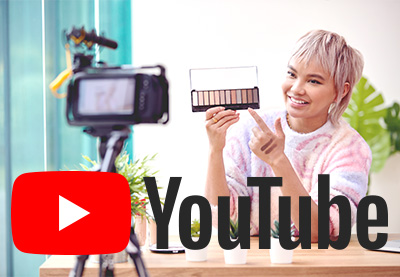
Welchen Font nutzt Youtube?
Es mag wie eine einfache Frage erscheinen: „Welche Schriftart verwendet YouTube?“ Aber die Antwort ist überraschend kompliziert, weil es verschiedene YouTube-Schriftarten gibt. Wir werden Ihnen in diesem Artikel alles erklären und einige alternative YouTube-Schriftarten durchgehen.
Welche Schriftart verwendet YouTube?
Die Schriftarten von YouTube variieren je nachdem, ob Sie über das Logo, Videotitel, Kommentare oder andere Bereiche der Website sprechen. Lassen Sie uns das nacheinander durchgehen.
Welche Schriftart verwendet YouTube für Videotitel?
Das ist recht einfach. Für Videotitel verwendet YouTube Roboto, eine sehr lesbare Schriftart, die Google für verschiedene Dienste wie Android, Google Maps und Google Play verwendet.
Beispiel der Schriftart Roboto via Wikimedia Commons
Welche Schriftart verwendet YouTube für Kommentare?
Für Videobeschreibungen und Kommentare verwendet YouTube auch Roboto. Bisher also alles einfach.
Welche Schriftart verwendet das YouTube-Logo?
Die Schriftart des YouTube-Logos sieht jedoch ganz anders aus als die Schriftart, die in den Kommentaren oder Videotiteln verwendet wird. Das liegt daran, dass es sich um eine völlig andere Schriftart handelt, und sie heißt YouTube-Logo.
Youtube-Logo-Schriftart
Youtube-Logo-Schriftart. Quelle: Wikipedia
Sie ist viel fetter und ziemlich kondensiert und ist tatsächlich eine modifizierte Version von Alternate Gothic, einer Schriftart, die Morris Fuller Benton im Jahr 1903 entworfen hat. Das Logo selbst wurde von YouTube-Mitbegründer Chad Hurley im Jahr 2005 entworfen.
Warum verwendet das YouTube-Logo eine andere Schriftart? Wie einer der Designer erklärt, erwies sich die neue YouTube-Schriftart als zu stark von dem ursprünglichen Logo abweichend, sodass sich das Unternehmen entschied, beim bestehenden Logo zu bleiben „als Hommage an unsere Vergangenheit“.
Um die Dinge noch etwas komplizierter zu machen. Es gibt auch verschiedene Versionen des YouTube-Logos für verschiedene Dienste, und einige verwenden überhaupt keinen Text. Hier ist zum Beispiel das Logo von YouTube Shorts:
Youtube-Shorts-Logo
Youtube-Shorts-Logo. Quelle: Wikipedia
Und was ist mit YouTube Sans?
YouTube hat auch eine eigene benutzerdefinierte Schriftart namens YouTube Sans, die es in Zusammenarbeit mit verschiedenen Designagenturen erstellt und 2017 eingeführt hat. Die Schriftart lässt sich von dem berühmten Wiedergabesymbol inspirieren und verwendet den gleichen Winkel, um Schnitte in einigen der Buchstabenformen zu erzeugen.
YouTube Sans
YouTube Sans. Quelle: Google Design
Das YouTube-Designteam hat im Laufe der Jahre seit 2017 subtile Änderungen an YouTube Sans vorgenommen, wie z. B. das Hinzufügen von abgerundeten und kursiven Versionen. Hier ist die YouTube-Schrift kursiv und abgerundet:
YouTube-Schrift kursiv und abgerundet
YouTube-Schrift kursiv und abgerundet. Quelle: Google Design
YouTube verwendet YouTube Sans tatsächlich nicht für sein Logo oder die Videotitel, Beschreibungen und Kommentare, aber es verwendet es in vielen seiner Marketingmaterialien und für andere Dienste außerhalb regulärer YouTube-Videos. Hier ist zum Beispiel die Landingpage von YouTube TV, die YouTube Sans für die eindrucksvollen Überschriften und Roboto für den Fließtext verwendet.
Youtube-TV-Seite
Nun, da wir alle Ihre Fragen zu den verschiedenen Schriftarten, die YouTube verwendet, beantwortet haben, werfen wir einen Blick auf einige coole Alternativen für die ikonische Schriftart des YouTube-Logos.
Alternativen zur YouTube-Schriftart
1. Denominary Condensed Font (TTF, OTF)
Eines der Dinge, die Sie an der Schriftart des YouTube-Logos bemerken werden, ist, dass sie ziemlich fett und kondensiert ist. Gerade diese Eigenschaften machen Denominary zu einer großartigen Alternative für die Schriftart des YouTube-Logos. Denominary umfasst über 480 Glyphen aus stilistischen Variationen, fakultativen Ligaturen, umfangreicher Sprachunterstützung und mehr.
2. Symfoner Modern Condensed Sans (TTF, OTF, WOF)
Eine großartige Wahl für Branding und das Erstellen von Logos, Symfoner Modern Condensed Sans ist eine YouTube-Alternative, die Ihnen gefallen wird.
3. Morgane Bold Condensed Sans (TTF, OTF, WOFF)
Werfen Sie einen Blick auf Morgane Bold Condensed Sans, wenn Sie ein Logo mit einer ähnlichen Stimmung wie das YouTube-Logo erstellen müssen. Diese saubere und moderne Schriftart eignet sich auch hervorragend für Titel, Beschilderung, Poster und alles andere, was Sie im Sinn haben.
4. Monetizer Condensed Sans (TTF, OTF)
Monetizer Condensed Sans ist eine dieser kühnen und modernen Schriftarten, die durch ihre Einfachheit auffallen. Diese großartige Schriftart eignet sich perfekt für eine Vielzahl von Anwendungen, von Titeln bis hin zu Branding.